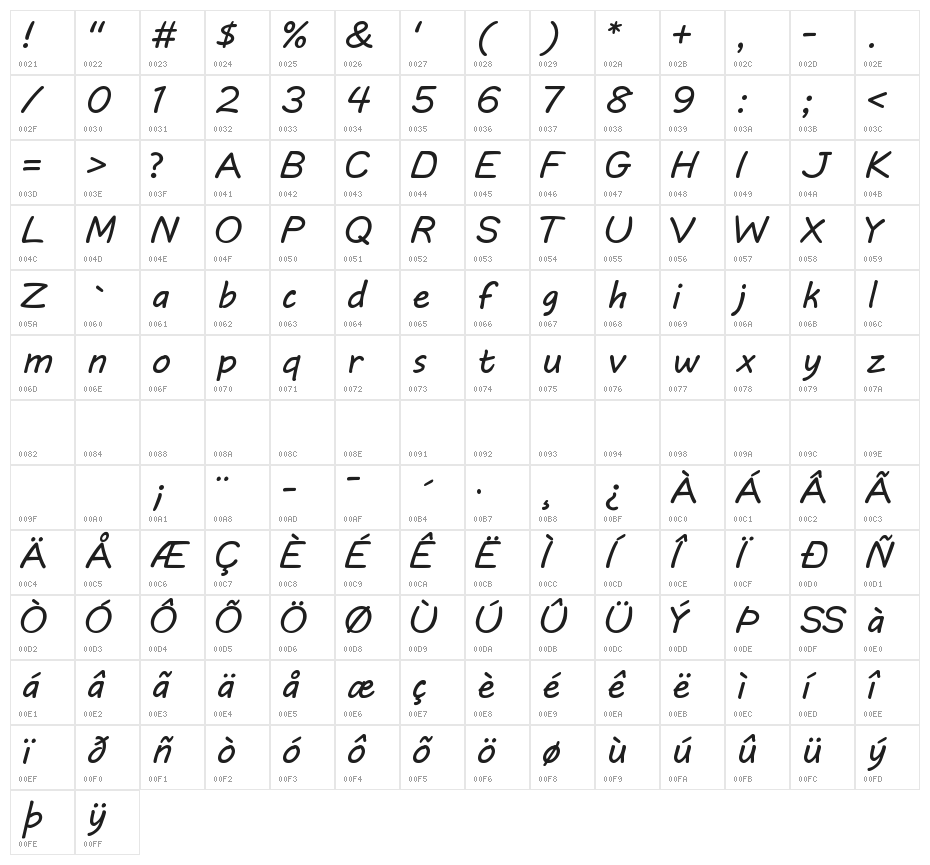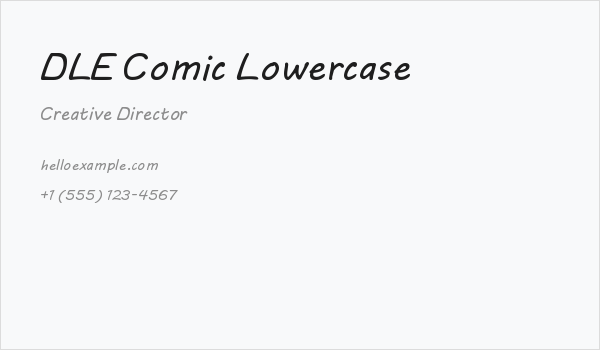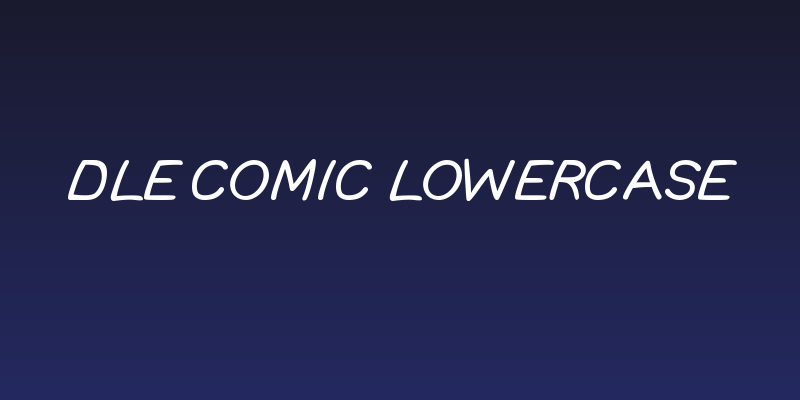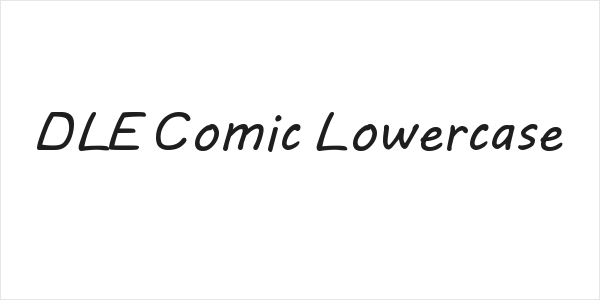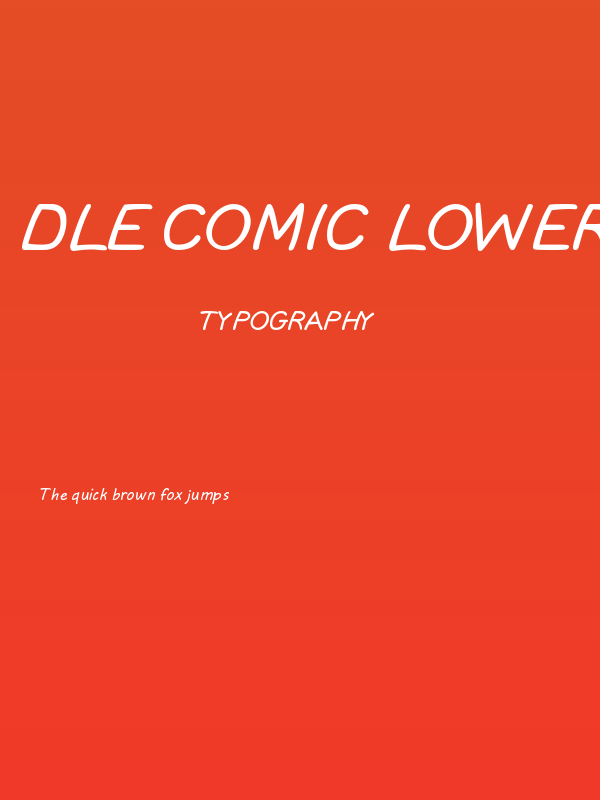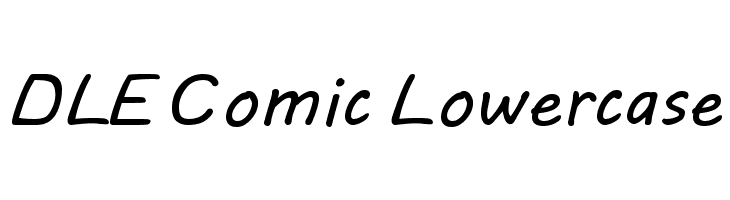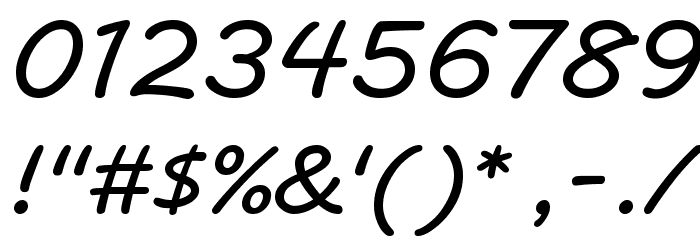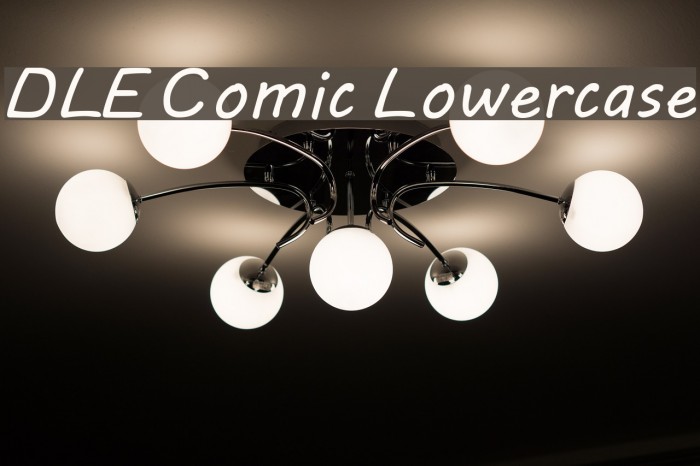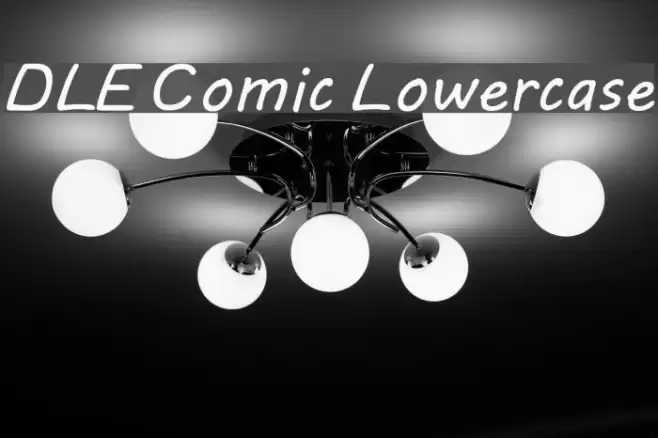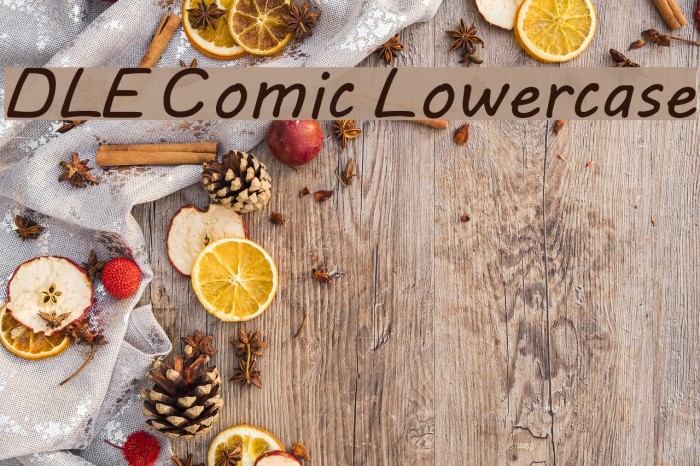
DLE Comic Lowercase Font
| Общий стиль | Casual and playful |
| Область применения | Headlines, Logos, Informal text |
| Рекомендуемые проекты | Ideal for comic books, children's books, playful branding, and informal designs. |